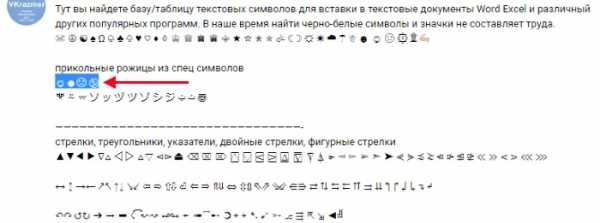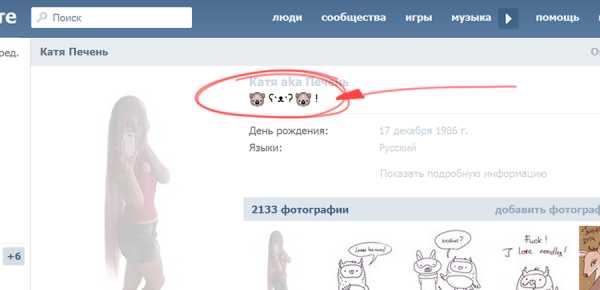
Статусы в ВК красивым шрифтом
Написанные статусы обычными буквами во ВКонтакте не так привлекают внимание, как буквы, созданные из символов и дополнены замысловатыми знаками. Каждый, наверное, видел такие на странице своих друзей. Такие надписи приковывают взгляд и часто вызывают восхищение. Прочитав эту статью, вы узнаете, как писать статусы в ВК красивым шрифтом.
Где взять статусы, написанные красивым шрифтом
Существует много специальных групп в VK, которые по заказу и часто бесплатно помогают пользователям получить статусы для своих страниц. Например, по адресу https://vk.com/mpp_top_gryppa вы сможете заказать необходимую фразу и указать автора, который ею займется. И через некоторое время вы получите в ответе нужную фразу замысловатыми символами. Здесь применяются как простые черно-белые шрифты, так и цветные картинки для украшения.
Все, что вам необходимо, это перейти на эту страницу группы и создать сообщение. В нем укажите автора и напишите статус или фразу, которую хотите увидеть в новом виде. Как можно заметить из даты создания сообщений на этой странице, модераторы отвечают достаточно быстро.
Если ввести в поиске запрос «Красивые шрифты» можно найти несколько групп, которые занимаются распространением самых разнообразных шрифтов и картинок. Они помогут вам дополнить задуманный статус самыми необычными символами.
Готовые символы и статусы ярким шрифтом в ВК
Известно, что социальная сеть ВКонтакте имеет самую молодую аудиторию среди всех подобных ресурсов. Она также считается одной из самых креативных и прогрессивных. Поэтому здесь можно найти множество тем с уже готовыми статусами в разных вариациях. В этой теме https://vk.com/topic-68859379_33597536 можно найти массу новых символов, миниатюр и картинок, которые помогут вам создать свою.